商用利用可能&動画にも使える!読みやすさ抜群!シネマフォント集【デザインカッツ】
今回は、本格的なシネマフォントからユニバーサルデザインフォントまで揃えた「読みやすさ抜群!シネマフォント集」。漢字もたっぷり使えて便利な日本語フォント集が驚きのプライスで購入できます。
「読みやすさ抜群!シネマフォント集」の気になる中身
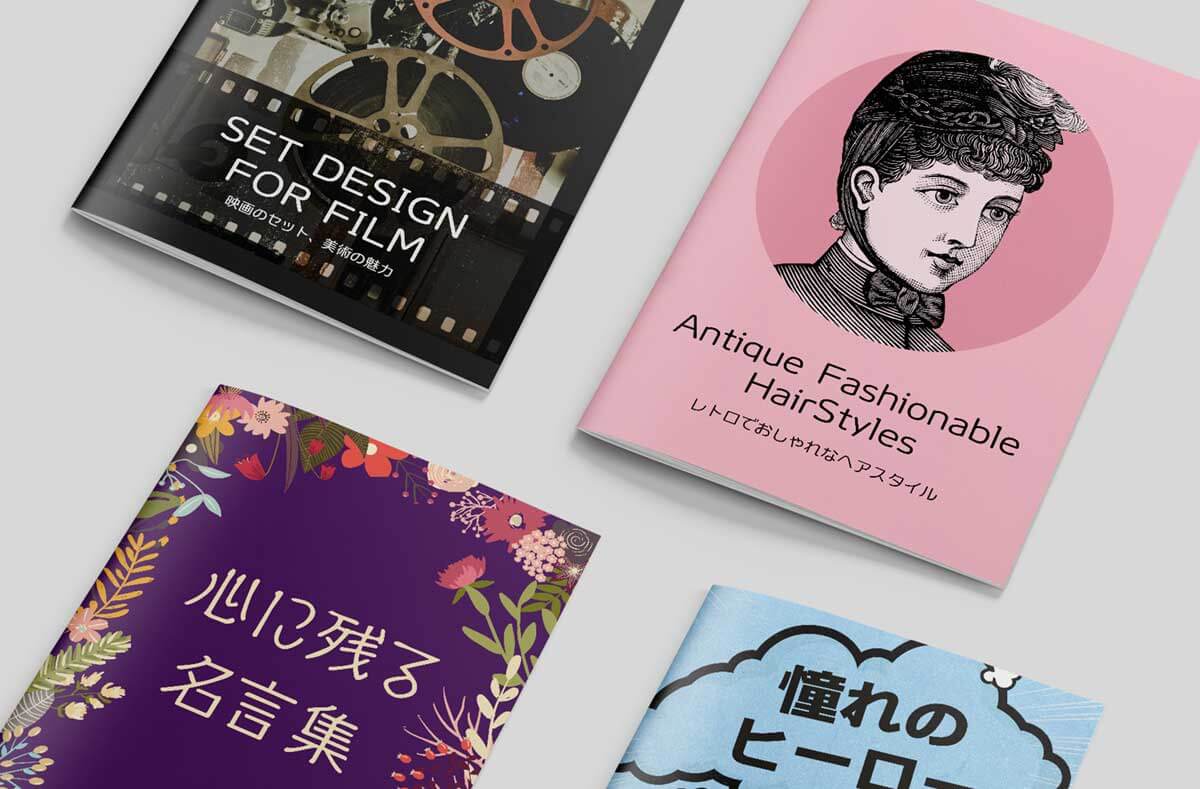
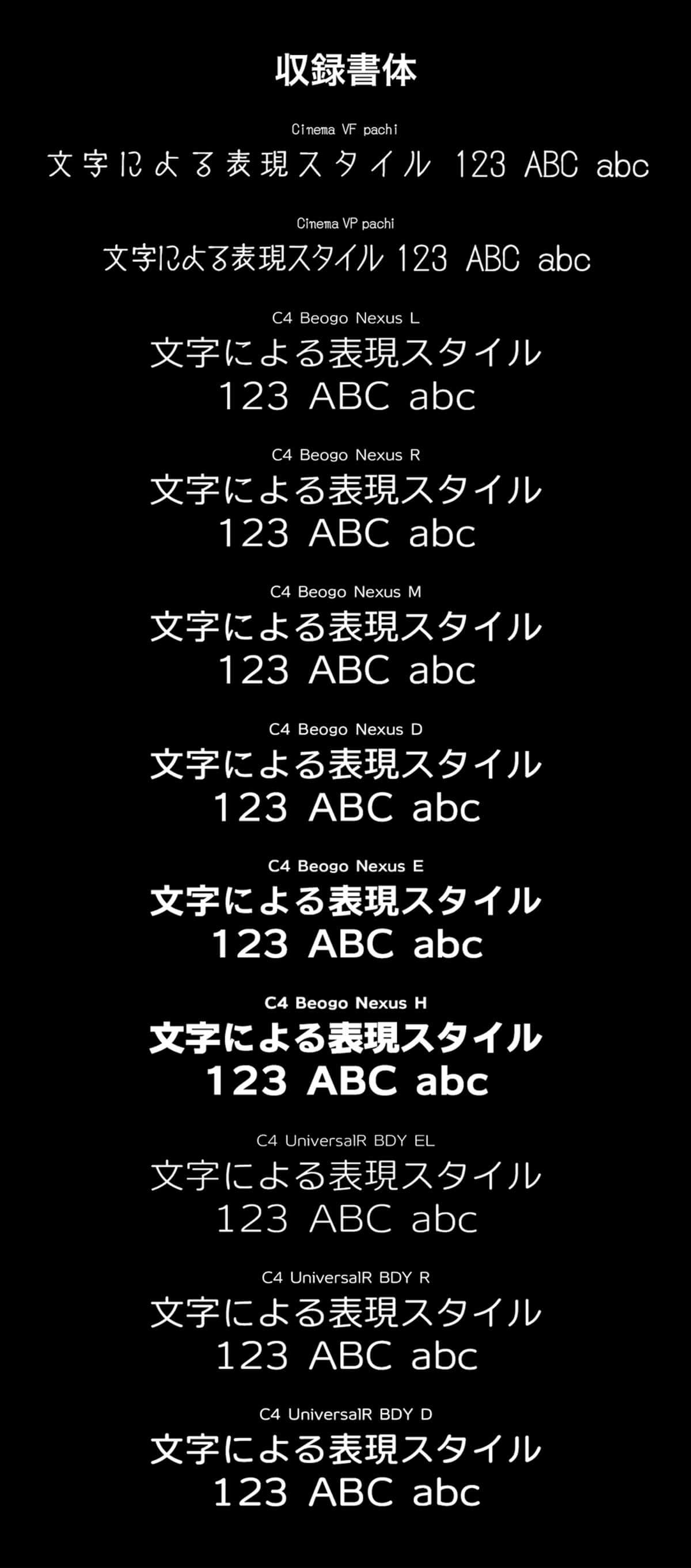
シネマ&ユニバーサルデザインフォントパック
シネマフォント
佐藤英夫氏デザインによる映画字幕用文字をPC向け用に開発したフォントです。日本で公開される数々の洋画の字幕に今もなお採用され続ける映画字幕用文字を限りなくオリジナルに忠実に再現した市販フォントとなります。このバンドルには、パチパチ文字を収録しています。
シネマフォントは動画のテロップ用途や本格的な手書き文字としてご利用いただけます。
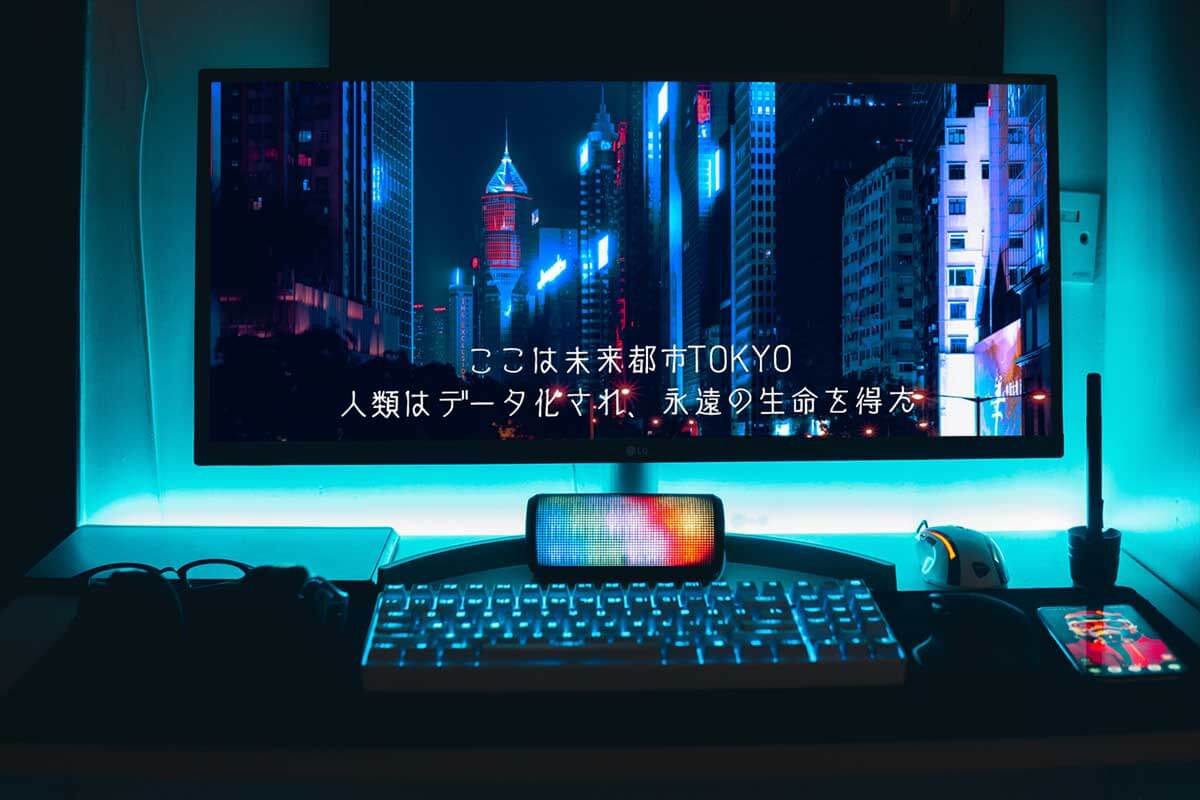
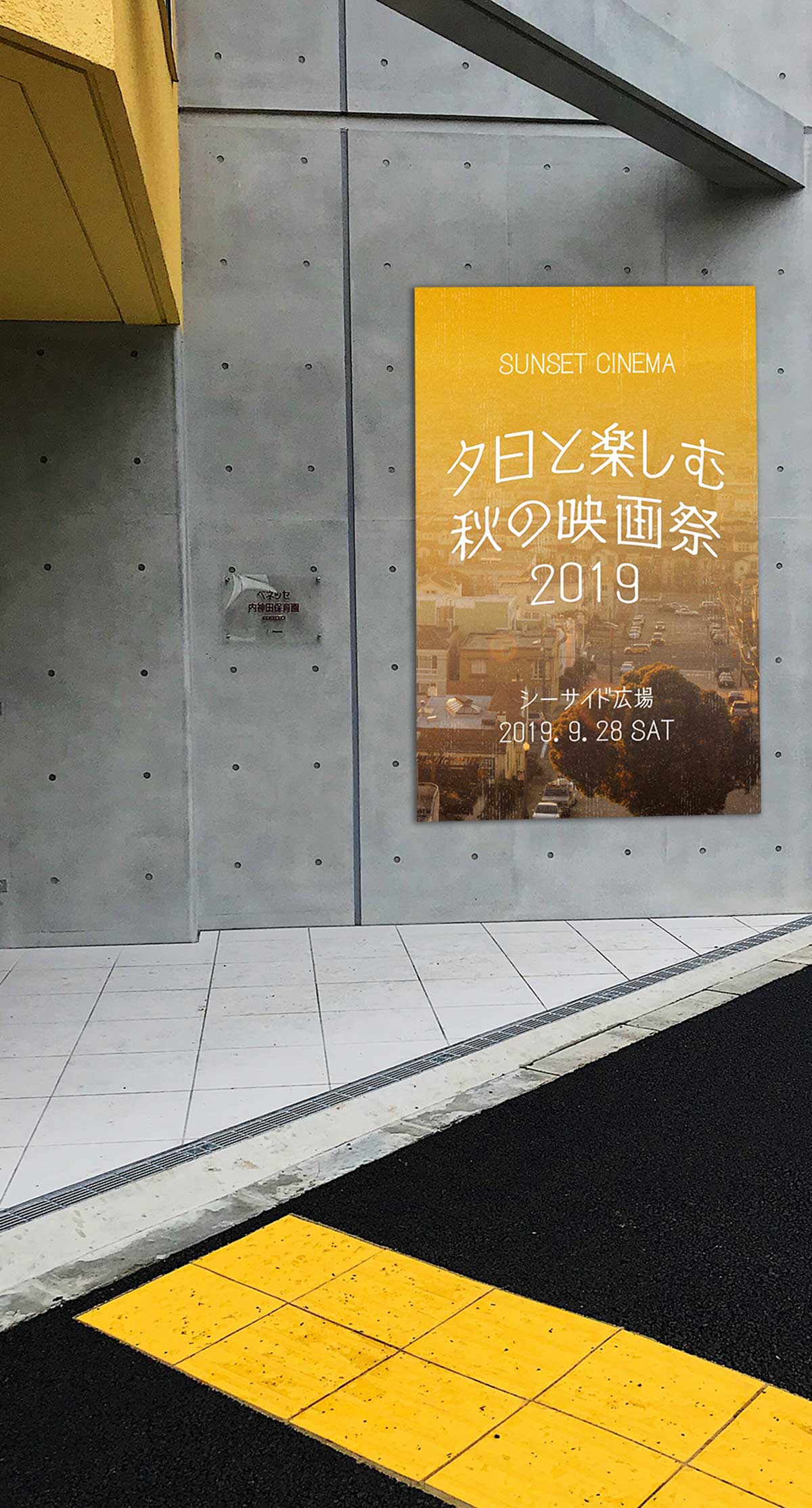
C4 ビオゴ Nexus
C4 ユニバーサルアールは、ユニバーサルデザインフォント(UDフォント)の基本丸ゴシック体です。
こちらのバンドルには、読む方にウェイトを置いた「BDY(ボディー)」をフォントファミリーで収録。